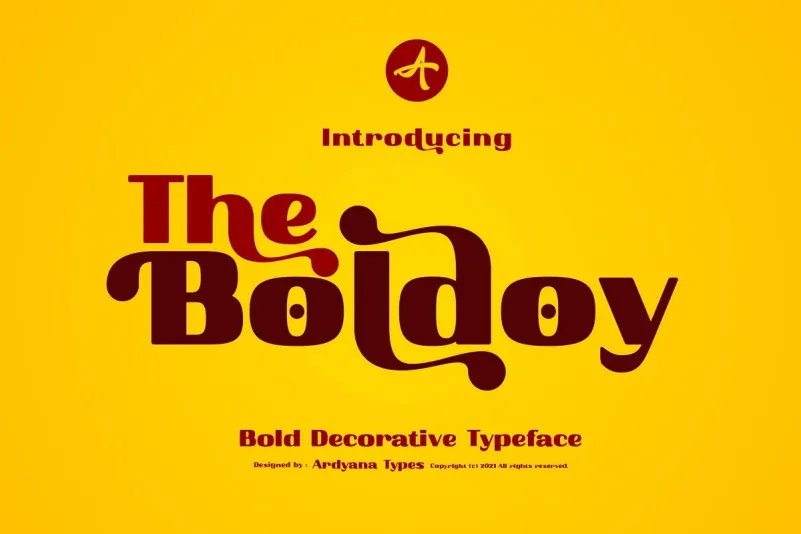
A Boldoy Font é uma tipografia sans-serif moderna e agressiva criada pelo Ardyanatypes, com características ágeis e energizantes. Seu design dinâmico permite que atraia a atenção de forma impressionante, especialmente quando usado em capas de material impresso. Quando adicionado à sua próxima campanha visual, ela fará as pessoas olharem, pois seu design descontraído e acolhedor evoca uma lembrança amigável da elefanta na primavera. Suave e alegre, essa fonte é perfeita para estilos de verão vibrantes, tornando-a um elemento essencial em qualquer projeto gráfico.